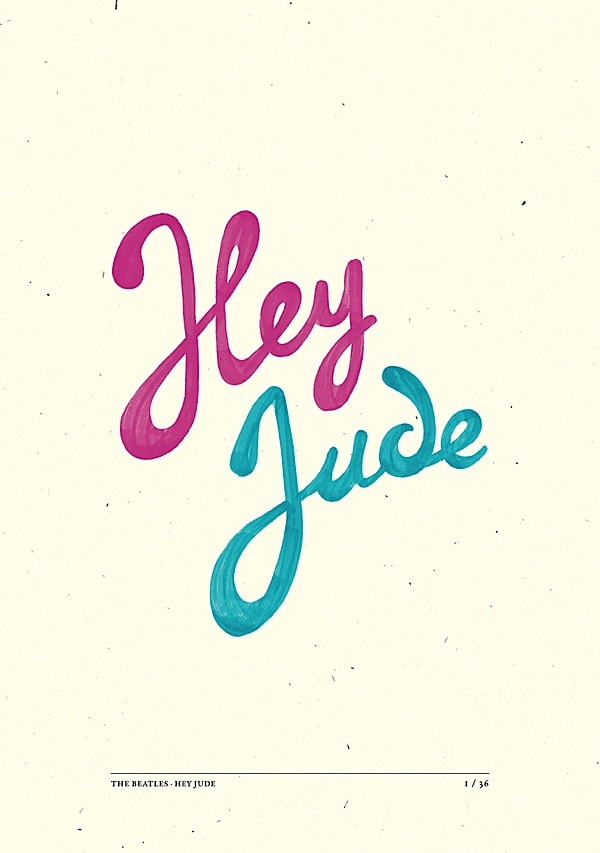
Ya en Diario THC hemos hablado muchas veces de que una tipografía puede cambiar el sentido de cualquier producto del diseño gráfico. Hoy hemos querido hacerlo de una forma gráfica, porque lo que les presentamos son precisamente 5 posters que juegan con las tipografías para un diseño de 10.
Nuestro primer poster tipográfico va dedicado a esos a los que les encantan las tipografías complicadas, las tipografías que esconden en su interior un diseño retorcido que encuentra su magia en lo más complejo. ¿Qué les parece?
El segundo poster tipográfico de hoy se basa más bien en tipografías hechas de dibujos, es decir, en tipografias que son un gráfico en si mismas.
Y si pasamos de lo más complejo a lo más sencillo con esta tipografía que ocupa el poster por completo de seguro que a más de uno le acaba encantando y se inspira en él en su próximo diseño
Pero no se nos podía olvidar que las tipografías están para lanzar un mensaje, y en este cuarto poster tipográfico queda más que claro que a veces el mensaje cuanto más bonito parece a la vista, mejor funciona
Si creen que nos íbamos a olvidar del estilo retro pop en Diario THC se han equivocado, y aquí el ejemplo que más nos ha gustado